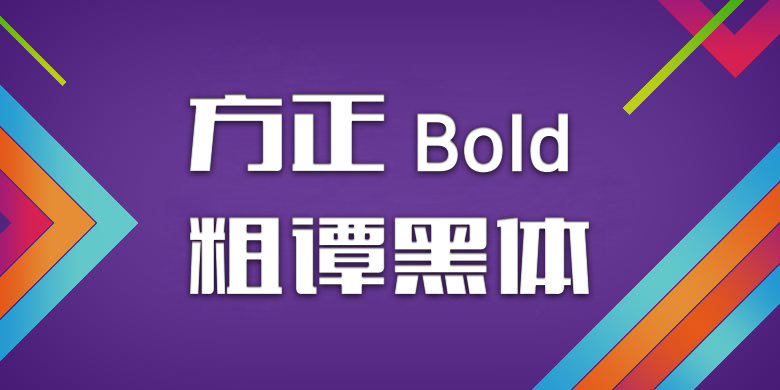
方正谭黑的设计是在对综艺体进行改造的过程中形成的。这款字体的重心很高,字形的外轮廓几乎贴近字面框,字形偏扁方。笔画由粗壮的几何直线构成,局部转折处呈圆角。方正谭黑家族包含粗、细两种字重,其中细体纯用直线设计,造型更加硬朗。方正谭黑家族设计感强,个性时尚,适用于商业品牌的广告、产品包装设计和影视作品。